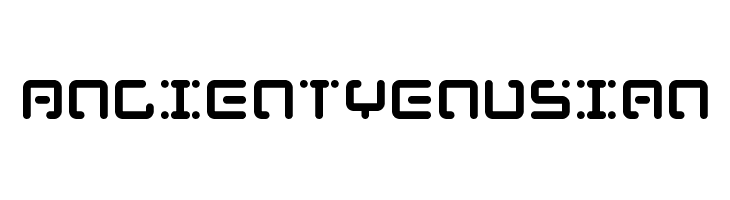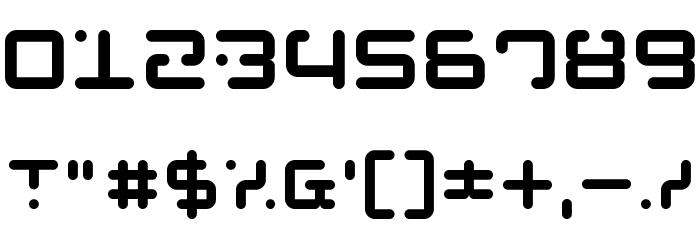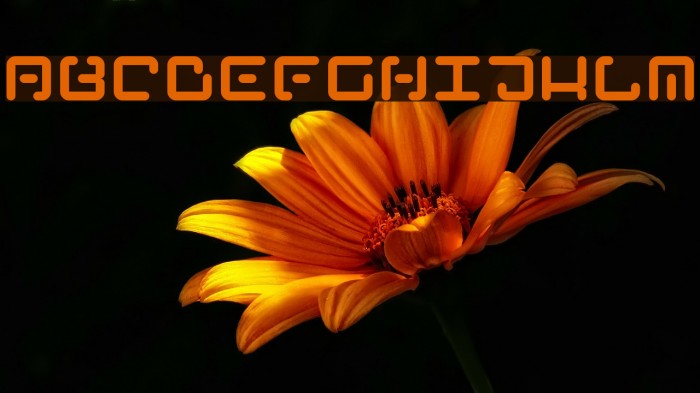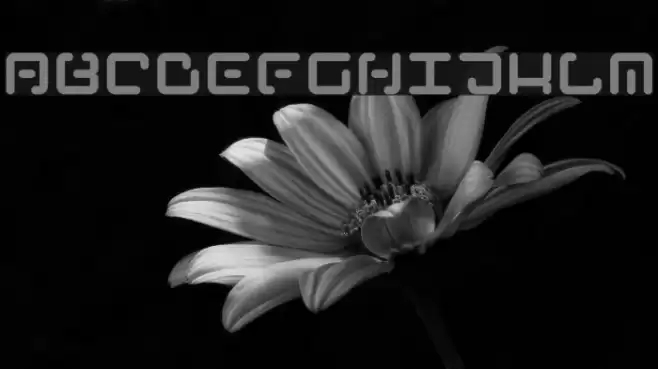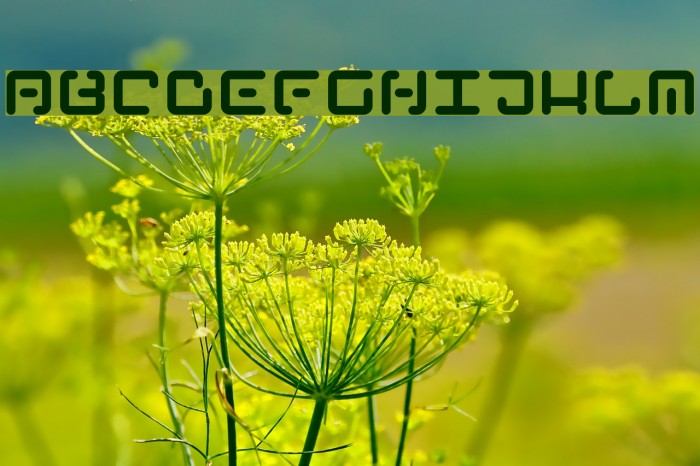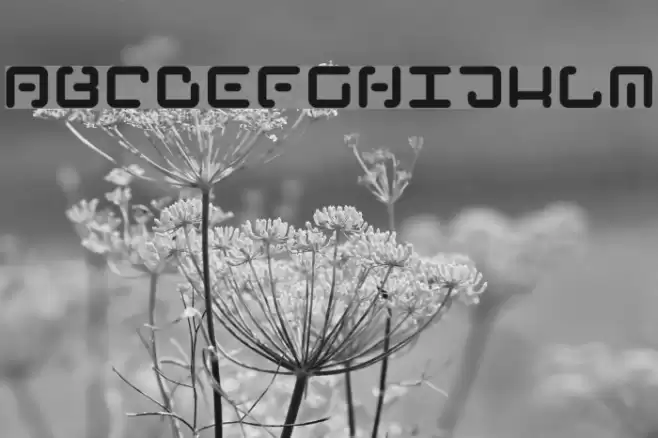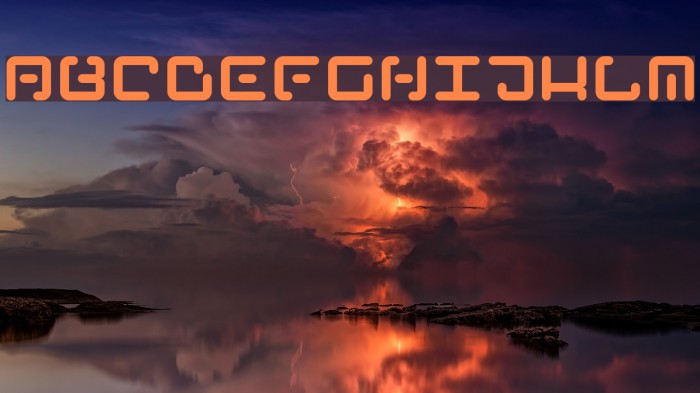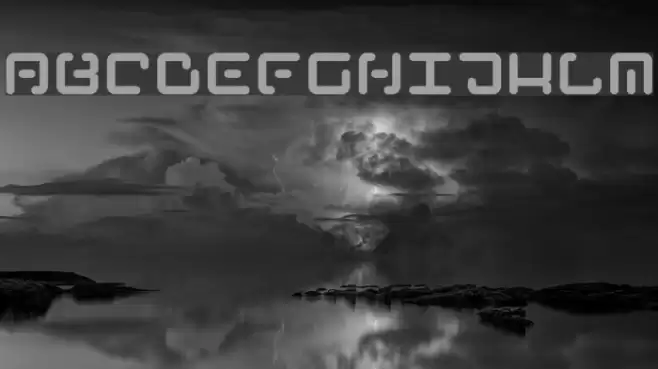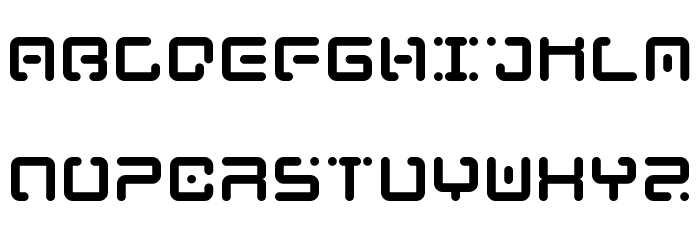
Ancient Venusian Font
✎ Futuristic
| श्रेणियाँ | Futuristic |
| उपयोग का मामला | Headlines, Logos, Digital interfaces |
| सुझाए गए प्रोजेक्ट | Ideal for sci-fi themed designs, tech branding, video game interfaces, and digital art projects. |